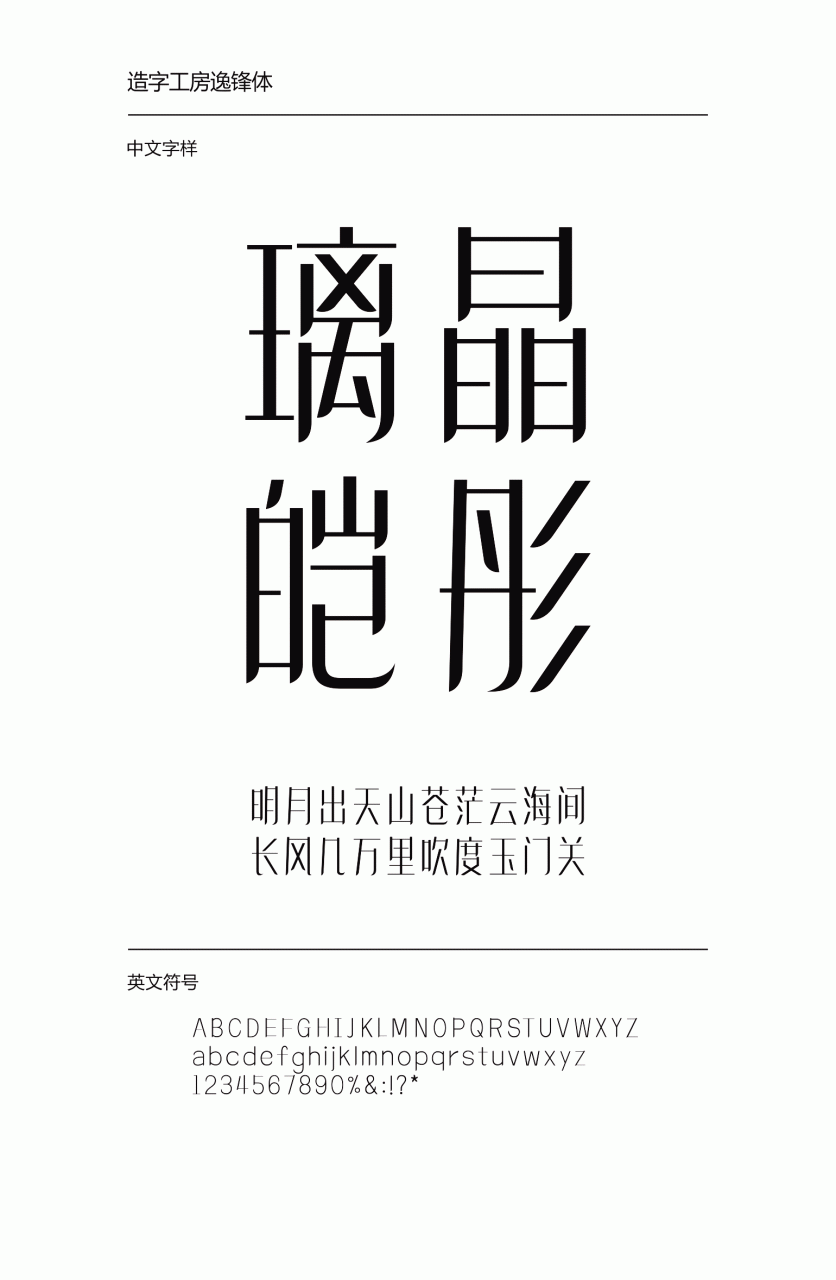
造字工房逸锋体,其字瘦长,笔触秀丽颀长,圆润顺畅,转折处快捷瘦劲,轻重顿挫、富有变化,风格柔丽知性,又不失刚韧,此款字体适用于时尚行业,主作标题与副标题之用。本字体为简体字库,采用OpenType/CID 格式, Adobe-GB1-5编码。基于中华人民共和国GB2312-80字符集标准, 另按需添加了 101 个汉字。共收容字数 6864 CJK 汉字,ASCII常用字符100个。